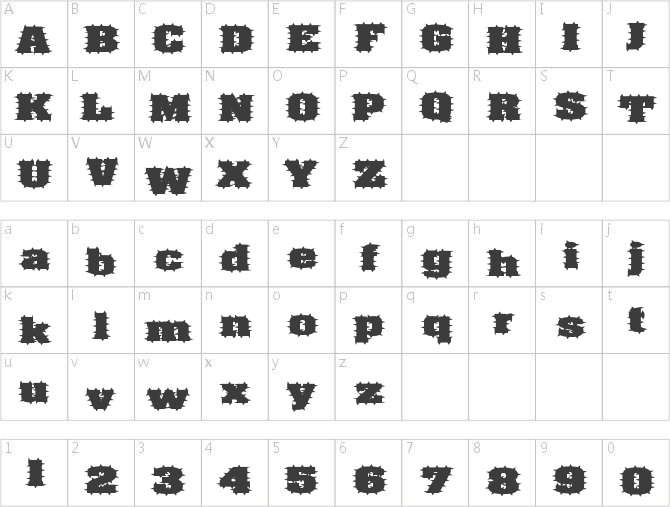
FZ BASIC 52 SPIKED EX
FZ BASIC 52 SPIKED EX介紹
FZ BASIC 52 SPIKED EX字體字庫是一款讓人賞心悅目、百看不厭的英文字體,適合各類廣告和產品包裝設計應用,字體大小0.09MB,格式為ttf字體,上傳用戶是黃肖,作者/版權方為未知
FZ BASIC 52 SPIKED EX效果圖